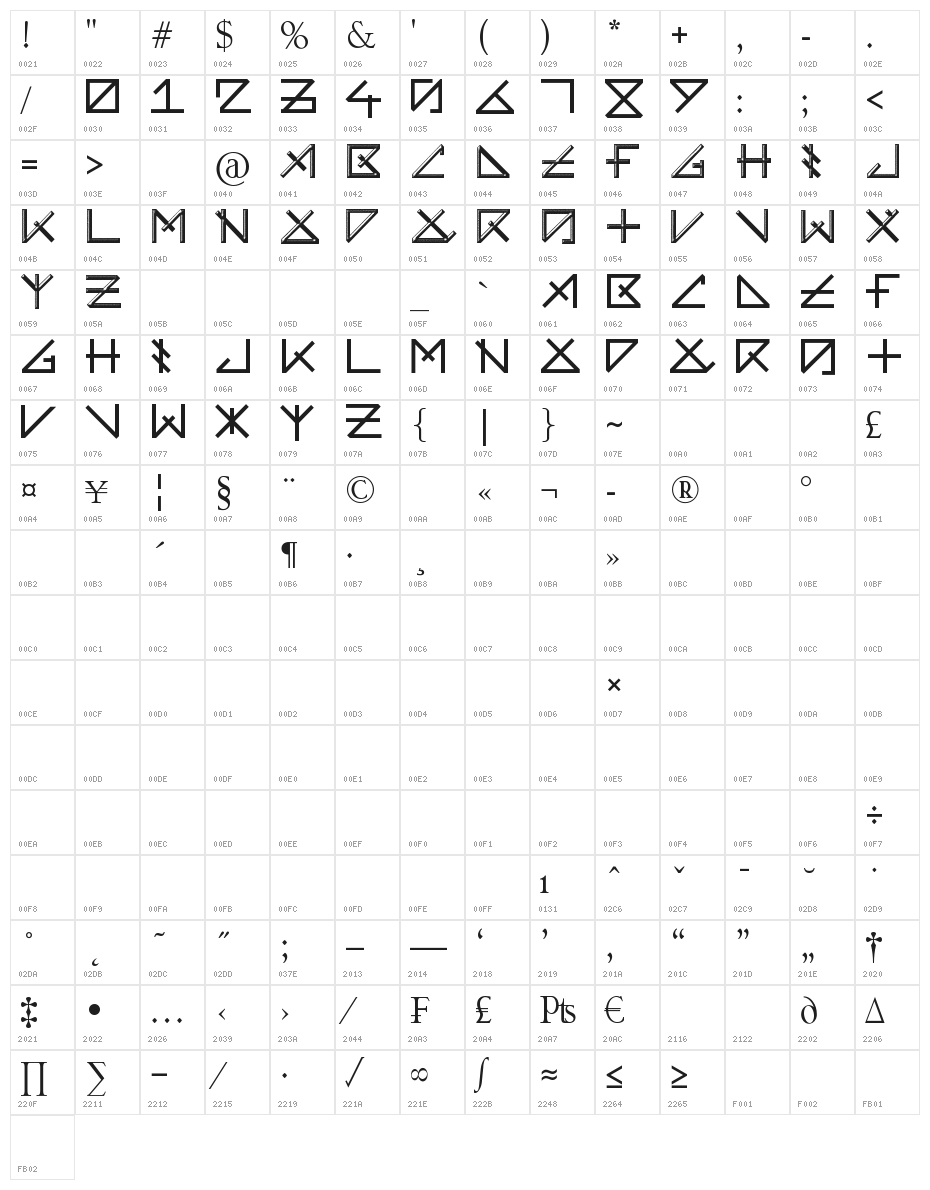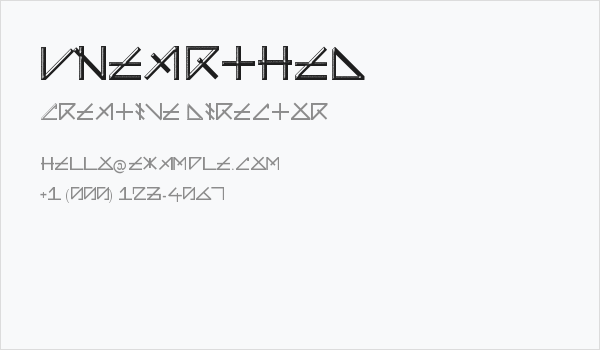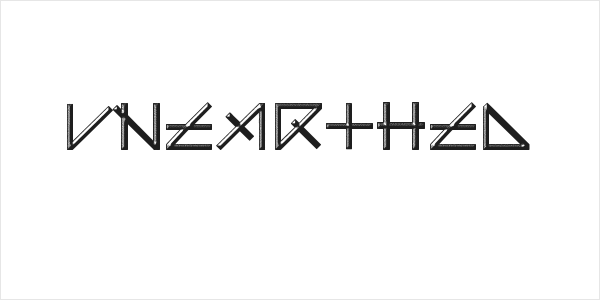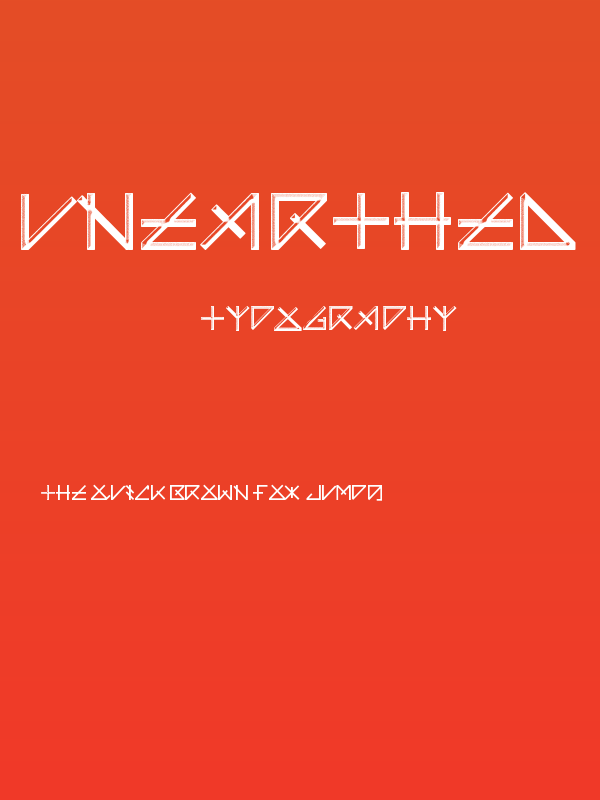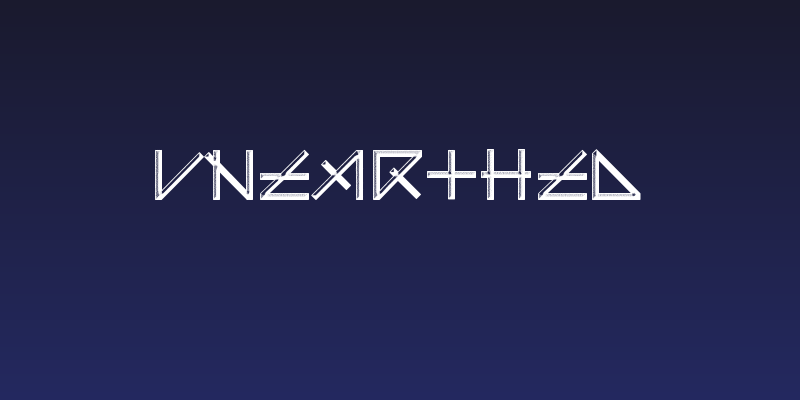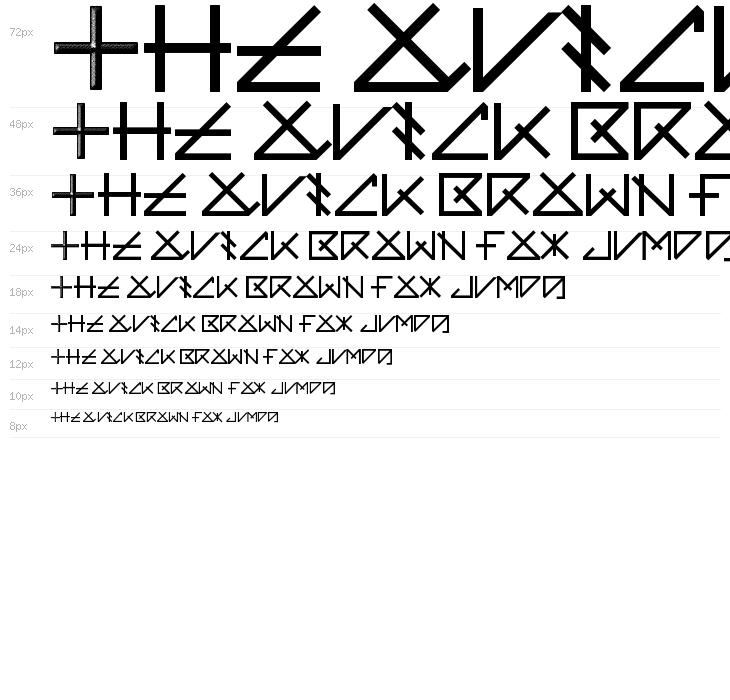
UNEARTHED Font
✎ Futuristic
| Gesamtstil | Futuristic, Modern |
| Anwendungsfall | Logos, Headlines, Posters |
| Vorgeschlagene Projekte | Ideal for sci-fi themed designs, tech branding, video game interfaces, and modern posters. |